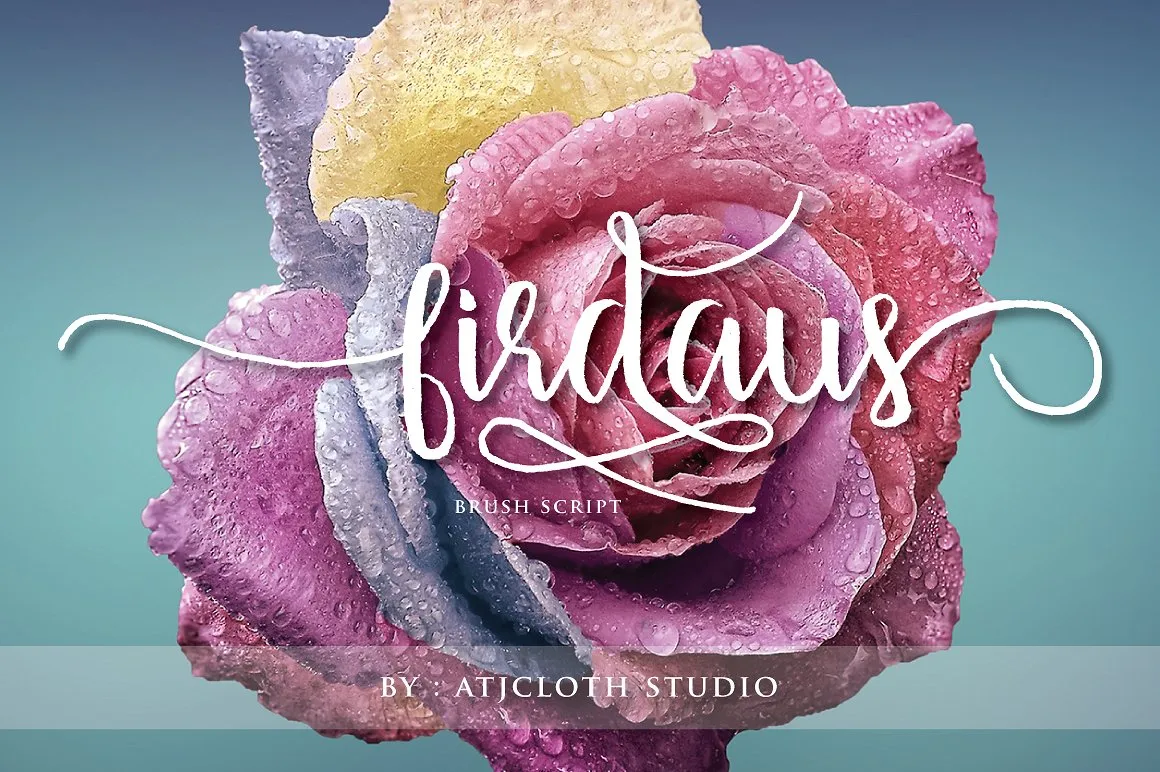
Firdaus Script é uma nova opção para a sua coleção de fuentes, especialmente indicada para projetos criativos que valorizam estilo elegante e moderno. Desenvolvida pelo estúdio Atjcloth Studio, esta fonte script possui um toque de calligrafia que traz frescura e originalidade ao seu design. Ideal tanto para promoção de produto como para expressar mensagens pessoais em cartões de aniversário ou notas degradê. Firdaus Script está repleta de recursos úteis, servindo perfeitamente para o uso em qualquer aplicação que exija um toque personalizado. Seja para criar materiais promocionais com quotes escritos a mão, embalagens de produto, rótulos, newsletters, cartazes, produtos de marca ou até mesmo materiais de marketing impressos, essa fonte oferece o necessário para transformar suas ideias em realidade. Esse tipo de personalização e atitude moderna é justamente o que distinguem Firdaus Script entre as demais fuentes do mercado. Com um estilo único e uma presença visual poderosa, esta fonte traz aos seus projetos a essência do design moderno e da arte da escrita. Não perca essa oportunidade de dar ao seu trabalho uma cara única e marcante com Firdaus Script.